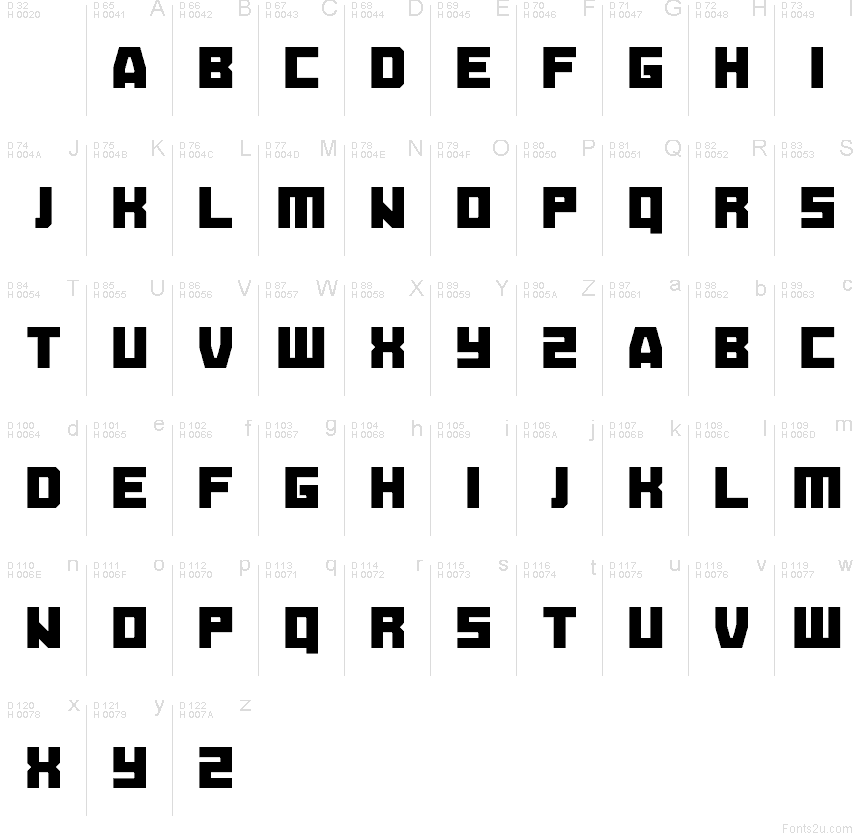
Frohburg Retro от Владимира Николича — это бесплатный ретро-техно шрифт для заголовков с высокими заглавными буквами, которые будто вырезаны из массивных прямоугольных блоков. Знаки выглядят так, словно пришли прямиком из ранних систем электронных логотипов: квадратные углы, глубокие вырезы и скошенные диагонали придают гарнитуре жесткий, механический и слегка игривый характер.
Этот шрифт отлично подходит для брендинга в стиле аркадных игр, заголовков на плакатах, обложек альбомов, игровых меню и графики для sci-fi мероприятий, где коротким словам нужно придать модульное, уверенное звучание. Как бесплатный шрифт, он также идеален для карточек с названиями, монограмм и компактных заголовков, так как заглавные буквы плотно складываются в сильную сетку, создавая запоминающийся силуэт.